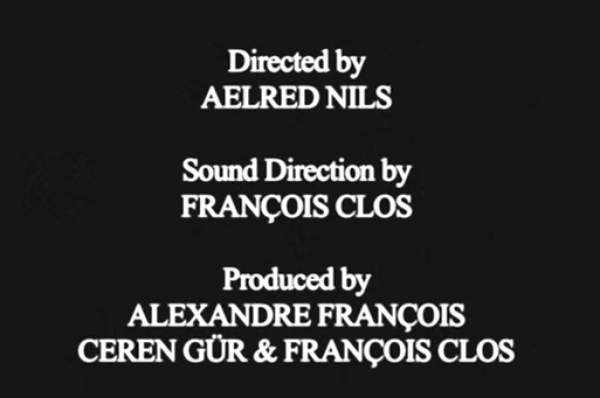
bu font nedir?
whatthefont'tan sonuç alamadım. nedir bu font acaba?
garalde (bold) olabilir
Bildigin Times New Roman bu sadece ekran screenshot oldugu icin bazi kenari kosesi daha yuvarlak gozukuyor.